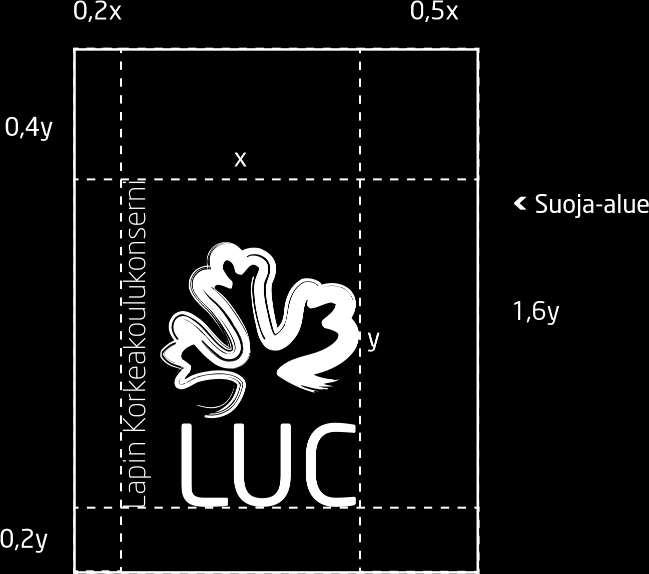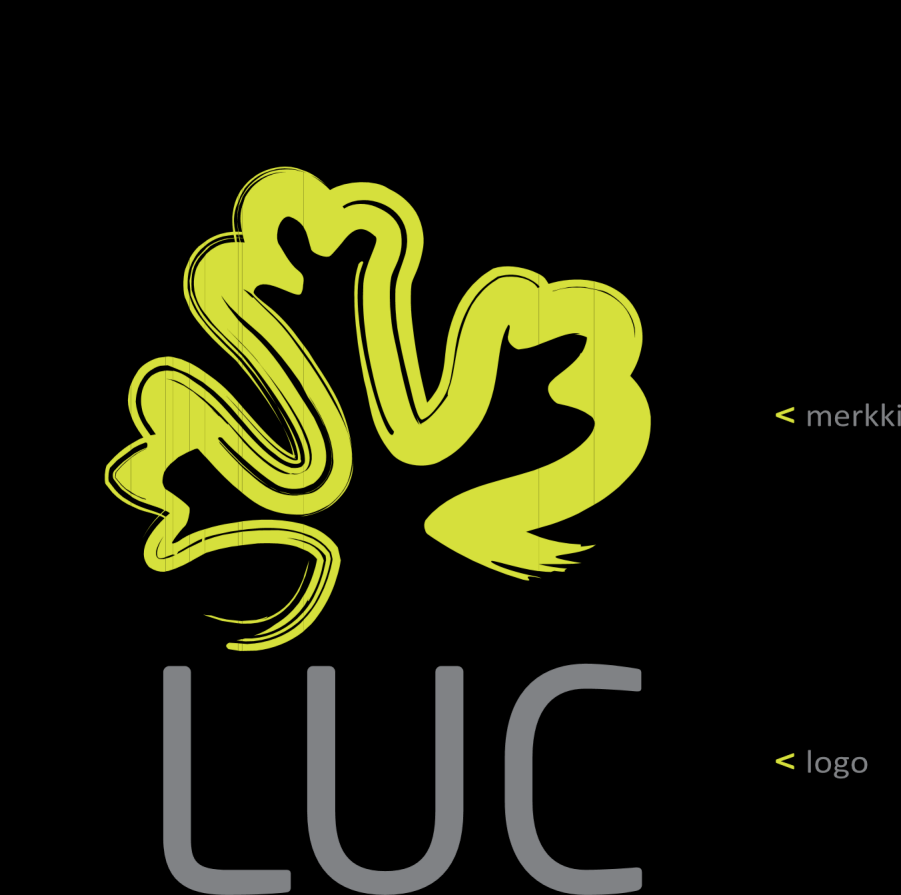
3 JOHDANTO Lapin korkeakoulukonsernin (LUC) graafisessa ohjeistossa olevat materiaalit löytyvät osoitteesta Kuvalliset ja kirjalliset viestit täyttävät maailmamme uusien ja perinteisten medioiden kautta. Tilanne luo jokaiselle yhteiskunnassa toimivalle ja viestivälle yritykselle, yhteisölle tai organisaatiolle uusia haasteita. Yhtenäinen ja laadukas visuaalinen ilme helpottaa sekä erottuvuutta, että viestintää, ja vahvistaa toivottua mielikuvaa organisaatiosta. Lapin Korkeakoulukonsernin visuaalisessa ilmeessä yhdistyvät nykyaikaisuus, kansainvälisyys ja laadukkuus luovuuteen ja yksilöllisyyteen. Vaikka konsernin ilme on kansainvälinen, merkkisuunnittelun juuret löytyvät lappilaisesta luonnosta ja orgaanisista jäkälämuodoista. Lapin Korkeakoulukonsernin merkin, logon ja muiden graafisten elementtien hallittu käyttö on olennainen osa konsernin viestintää. Graafinen ohjeisto opastaa käyttämään uutta tunnusta sekä muita keskeisiä elementtejä yhtenäisellä ja laadukkaalla tavalla. Graafisen ohjeiston avulla halutun ilmeen säilyttäminen onnistuu myös ihmisten ja tehtävien vaihtuessa. LUCin typografia uudistettiin kesäkuussa LUCin graafinen ohjeisto päivitettiin keväällä 2016.
5 LOGO JA MERKKI Jäkälälogon perusteita teemavalinnan näkökulmasta: Monimuotoinen jäkälä muodostaa kauniita, monen eri lajin värikkäitä kasvustoja korkeimmillekin tunturihuipuille eli sinne, missä muut elolliset eivät pärjää. Jäkälä edustaa Lappia, pohjoisuutta yleensä, kestävyyttä (laatua), kukoistusta ja yhdessä toimimisen voimaa. Hennonvihreänä elävänä organismina se kertoo jatkuvasta kasvusta ja kehittymisestä. Tietty sukulaisuus paljon käytetyn lumihiutaleen kanssa tuo logoon tarkoitettuja, visuaalisia yhtymäkohtia. Jäkälälogon perusteita visuaalisuuden näkökulmasta: Lapin korkeakoulukonserni on monipuolinen yhteisö joka toimii eripuolilla Lappia ja viestii maailmanlaajuisesti. Kaikkia konsernin osia kuvaava ja kaikille sopiva visuaalinen ilme on sidottu abstraktilla tasolla esitettyyn jäkälään. Merkissä tärkeintä ovat sen muodostamat mielikuvat, ei niinkään selkeä visuaalinen yhteys kiven pinnalla kasvavaan jäkälään, joka on jo itsessään muotona orgaaninen ja muuttuva. Merkin teho perustuu kahden visuaalisen muotokielen yhdistämiseen. Typografian geometriset ja modernit muodot ilmentävät konsernin uskottavuutta yhteiskunnallisena ja kansainvälisenä toimijana, korkealaatuisen koulutuksen tarjoana ja yritysmaailman kumppanina. Typografian tavoiteltuja mielleyhtymiä: nykyaikainen, bisnes, ammattimainen. Jäkälän orgaaniset muodot puolestaan tuovat merkkiin omaleimaisuutta konsernin erottuvuustekijöiden mukaisesti. Merkitystasolla jäkälä sitoo tunnuksen lappiin, muotokielen assosiaatioiden tasolla luovuuteen, onhan jäkälä kuin siveltimellä maalattu. Lisäksi epätäydellinen (vrt. geometrinen, symmetrinen) muoto tuo tunnukseen inhimillisyyttä. Merkkiosan tavoiteltuja mielleyhtymiä: luonto, raikkaus, luovuus, persoonallisuus.
6 Lapin korkeakoulukonsernin visuaalinen ilme perustuu tunnukseen, joka on jäkälämerkin, LUC -logon ja Lapin Korkeakoulukonserni -tekstin ydistelmä. Tunnuksen asemesta tietyissä kohteissa voidaan käyttää pelkkää logoa (ks. kansi, ks. yksikköbrändisovellus). Merkkiosaa ei saa käyttää yksinään korvaamassa tunnusta tai logoa, osana kuvitusta sitä voi käyttää. (ks. edellinen aukeama)
7 VÄRIMAAILMA vihreä Vihreä on pääväri valossa (additiivinen järjestelmä), mutta ei pigmenteissä (subtraktiivinen järjestelmä). Huolimatta siitä, että vihreää esiintyy luonnossa niin paljon, väripigmenttiä on hankala valmistaa. Useissa kulttuureissa vihreä on elämän ja kasvun merkki, se liitetään vehreään luontoon ja luonnon henkiin heräämiseen. Politiikassa vihreä yhdistetään ekologisiin näkökohtiin. Sanotaan, että vihreä on ihmissilmälle kaikkein rauhallisin väri. LUCin vihreä on kirkas tehosteväri, jonka voi toistaa painotuotteissa oikein vain PMS -värejä käyttämällä, sähköisissä medioissa värin käyttö ei ole rajoitettu. Juuri oikean sävyn löydät kun vaellat sateen jälkeen Lapin tunturirakoilla, mustan harmaasta maassa kiven pinnalla oleva jäkälä on melkein luonnottoman kirkas. Sanomalehti-ilmoituksissa ym. kohteissa, joissa PMS -värin käyttö ei ole mahdollista, käytetään CMYK vihreää. Harmaa Kahden ääripään, mustan ja valkoisen, sekoituksena harmaasta on tullut kompromissiväri. Ittenin mukaan harmaa saa merkityksensä vain vieressä olevilta väreiltä - esim. musta tekee siitä elegantin. Harmaa on yksittäisenä värinä tavallinen ja yllättämätön. Samalla se on varma, tekninen ja luotettava. Pukeutumisessa harmaa puku miehillä on melko varma valinta, jos ei tiedä, millaisia tilanteita päivällä on tulossa. Lapin Korkeakoulukonserni -teksti on 100% musta. < 60% musta < PANTONE 381 U < 100% musta < C27 M0 Y91 K0
8 TYPOGRAFIA LUC:n virallinen Logotyyppi on Neo Sans Regular versaalina ladottuna. (Huom. Neo Sans Regularia käytetään vain logon yhteydessä) Logon väri on 60% musta. Lapin Korkeakoulukonserni on ladottu Neo Sansin Light -leikkauksella. Lapin korkeakoulukonsernin pääfontti on Roboto ja apufonttina on Libre Baskerville. Robotoa käytetään kaikissa LUCin materiaaleissa, sekä verkossa, Microsoft Office ohjelmissa, että painosovelluksissa. Libre Baskervillea käytetään mausteena erilaisissa painosovelluksissa, mm. italic-leikkausta ingresseissä (esim. lehtiilmoiutukset ja rollup). Vara-Officefonttina LUCilla on käytössä CALIBRI. Calibria käytetään varafonttina Microsof Office-ohjelmissa (esim. Word ja PowerPoint), jos Roboto ei niissä toimi upotettuna. Graafinen ohjeisto on jo itsessään kattava esimerkki typografian käytöstä. Graafisen ohjeiston leipätekstin (Roboto) koko on 10 pistettä ja riviväli 14 pistettä. Pääotsikkotyyppi (Roboto versaalina, väri 60% musta) on kokoa 36 pistettä. Pääfontti: ROBOTO (Google Fonts) Käytetään kaikissa LUC:in materiaaleissa, sekä verkossa, Microsoft Office ohjelmissa, että painosovelluksissa Roboto Thin + Thin Italic Roboto Light + Light Italic Roboto Regular + Regular Italic
9 Roboto Medium + Medium Italic Roboto Bold + Bold Italic Roboto Black + Black Italic Apufontti: LIBRE BASKERVILLE (Google Fonts) Käytetään mausteena erilaisissa painosovelluksissa, mm. italic- leikkausta ingresseissä (esim. lehtiilmoitukset ja rollup) Libre Baskerville Regular Libre Baskerville Italic Libre Baskerville Bold abcdefghijklmnopqrstuvwxyz
10 Vara-Officefontti: CALIBRI (Microsoft-ohjelmien mukana tuleva fontti) Calibria käytetään varafonttina Microsof Office-ohjelmissa (esim. Word ja PowerPoint), jos Roboto ei niissä toimi upotettuna Calibri Regular Calibri Italic Calibri Bold Italic
11 TUNNUKSEN KÄYTTÖ Lapin Korkeakoulukonsernin visuaalinen tunnus on ulkoasultaan nykyaikainen ja aktiivinen. Jotta tunnus toimii suunnitellulla tavalla, on sen käytössä otettava huomioon tunnuksen suoja-alue ja tausta, jolle tunnus asetetaan. Tunnuksen elementtien (merkki, logo, Lapin Korkeakoulukonserni -teksti) lisäksi tunnuksessa neljäs olennainen elementti on tyhjä tila merkin yläpuolella. Tunnusta käytettäessä olennaista ei ole niinkään laskea tarkkoja mittasuhteita suoja-alueelle vaan huolehtia, että merkki saa riittävästi tilaa ympärilleen, etenkin tunnuksen oikealla- ja yläpuolella. 1,7x < Tunnuksen pienin käytettävä koko, leveys 15 mm Tätä pienemmissä käyttökohteissa sovelletaan pelkkää LUC-logoa. LUC-logon saa tarvittaessa viestintäsuunnittelijalta.
13 TUNNUKSEN KÄYTTÖ Visuaalinen ilme esiintyy kaikissa konsernin materiaaleissa, joko varsinaisella tunnuksella tai logolla. Yksiköt viestivät edelleen omalla visuaalisella ilmeellään, LUC näkyy allekirjoittajana kunkin liikemerkin yhteydessä. Logo on ulkoasultaan neutraali ja sopii siten hyvin yhdistettäväksi osaksi erilaisia ilmeitä ja tunnuksia. Kirjaston, Sociopoliksen, Matkailualan tutkimus- ja koulutusinstituutin, Pohjoisen kulttuuriinstituutin ja Palvelut -tukitoiminnon tunnukset ovat suoria sovelluksia itse konsernin ilmeestä. Vaikka tunnukset ovat yhtä vahvaa perhettä, voidaan palvelubränditasolla luoda kullekin toimijalle persoonallisuus muilla visuaalisilla sovelluksilla. Esimerkiksi Matkailuinstituutin opiskelijoille suunnattu webkampanja voi soveltaa hyvinkin omanlaistaan ilmettä.